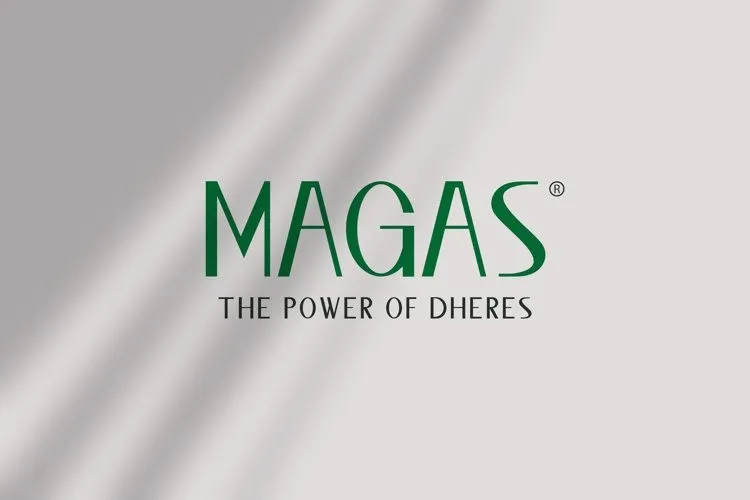
Magas Font é uma elegante tipografia sans-serif desenvolvida pelo estúdio evloxx studio, inspirada nos estilos atuais e contemporâneos. Sua simplicidade e estilo sofisticado a tornam ideal para um amplo range de projetos como logomarcas, convites, relatórios financeiros e folhetos. Com sua capacidade de se adaptar a quase todos os ambientes de projeto, Magas Font oferece uma opção perfeita para designers buscando o equilíbrio entre simplicidade e beleza. Seu design atemporal faz dele uma fonte versátil que não apenas combina bem com tendências modernas, mas também oferece um toque de elegância a qualquer projeto de identidade visual ou design gráfico. Em sua busca por uma fonte perfeita para seu próximo projeto, Magas Font provavelmente será o parceiro ideal, combinando facilidade e sofisticação na medida certa.